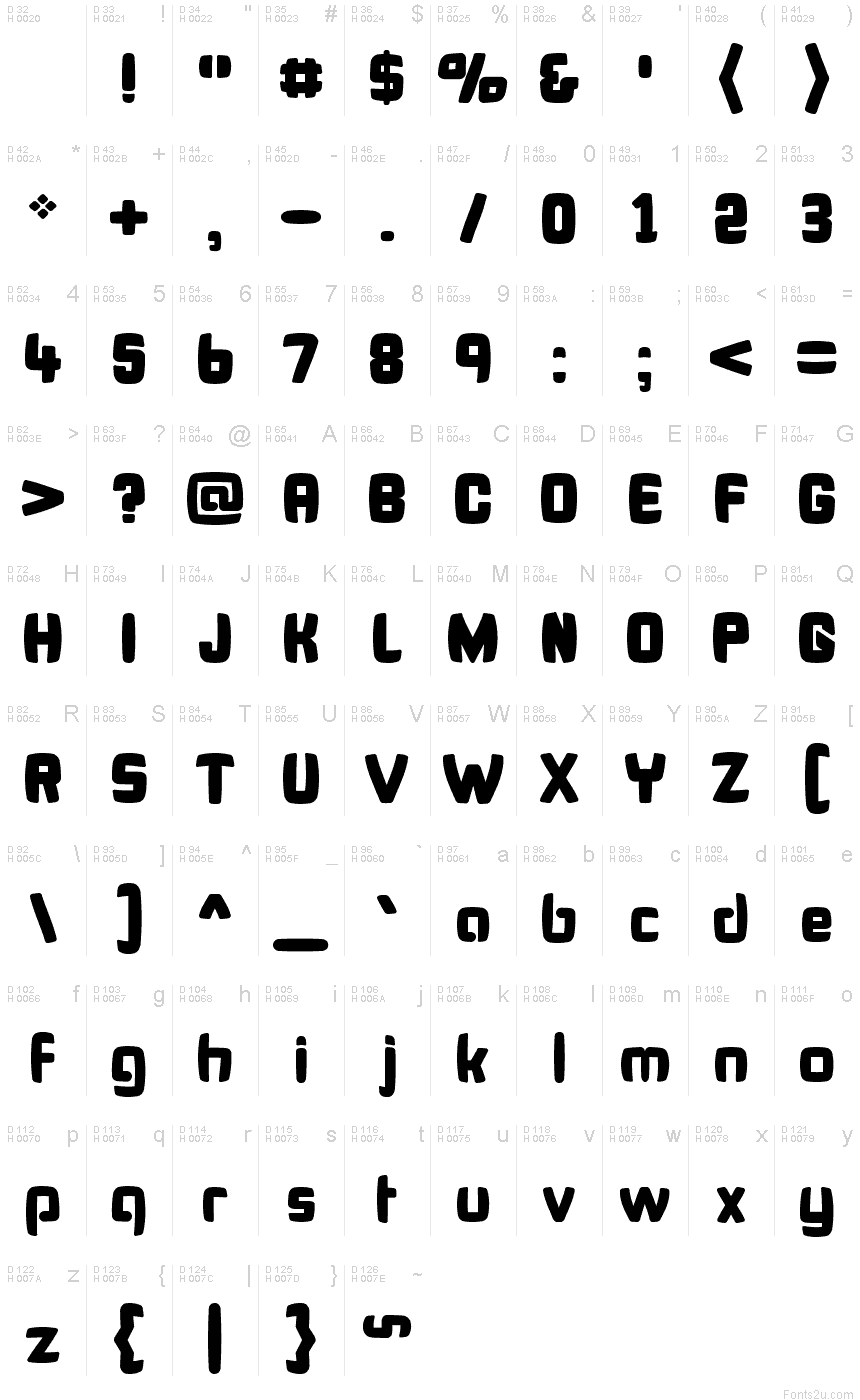
Bonk Fatty autorstwa Rolfa Schoebera z GemFonts to darmowy, komiksowy krój display, wyróżniający się wielkimi, pulchnymi literami, które wyglądają jak napompowane powietrzem. Wyraziste, „tłuste” kształty, ciasny odstęp i lekko drżące krawędzie nadają mu głośny, kreskówkowy charakter – niczym efekt dźwiękowy zamrożony w trakcie „bonk!”.
Dzięki Bonk Fatty nagłówki i logotypy zyskują natychmiast skoczny i zabawny klimat. Ten darmowy font świetnie sprawdzi się na okładkach książek dla dzieci, opakowaniach przekąsek lub zabawek, w komiksowych dymkach, miniaturach YouTube, zaproszeniach na imprezy, a także na zabawnych koszulkach czy naklejkach. Używaj go w dużym rozmiarze, dbaj o krótkie teksty i zestaw z prostym, zaokrąglonym krojem bezszeryfowym, aby te masywne kształty przyciągały wzrok.